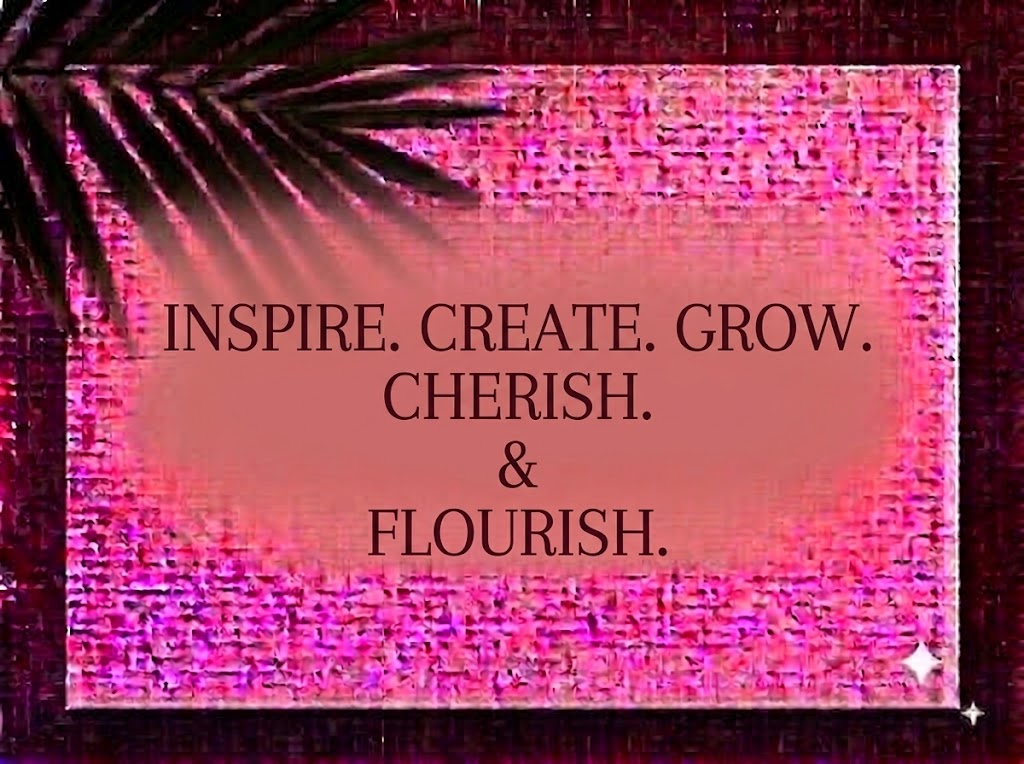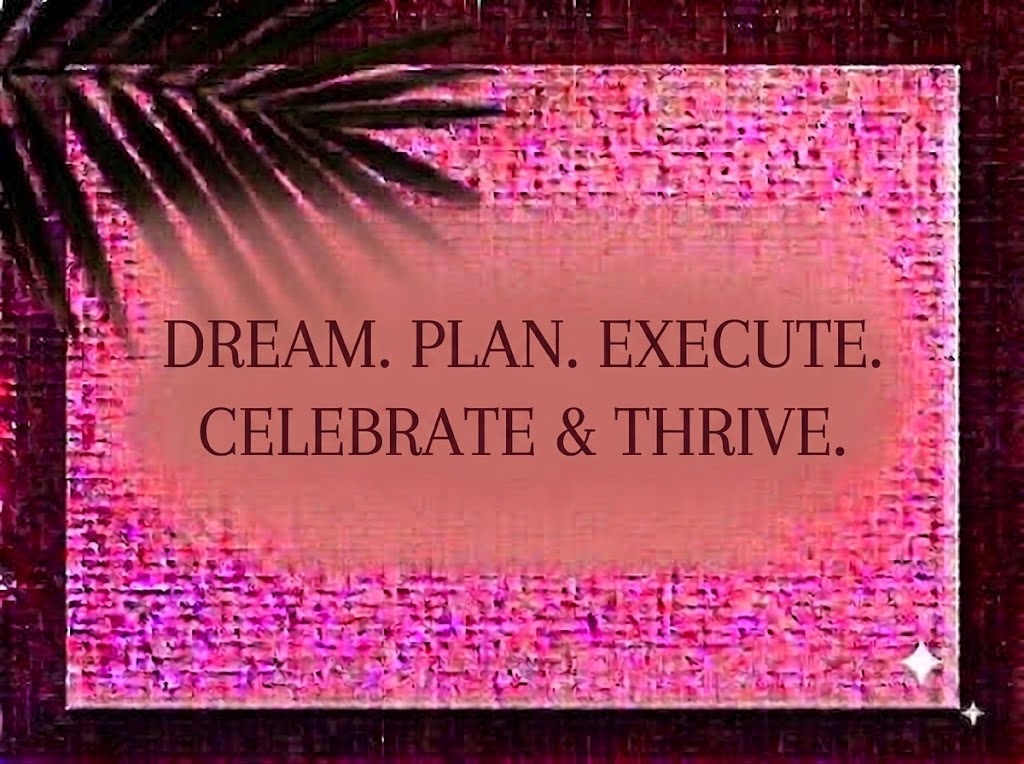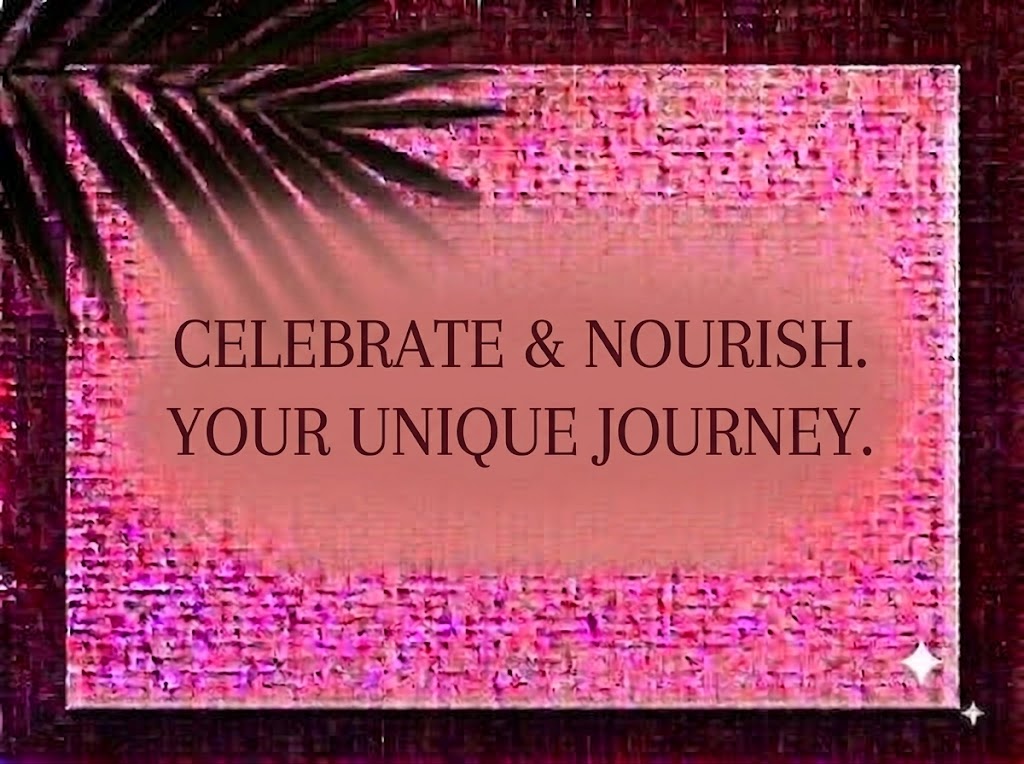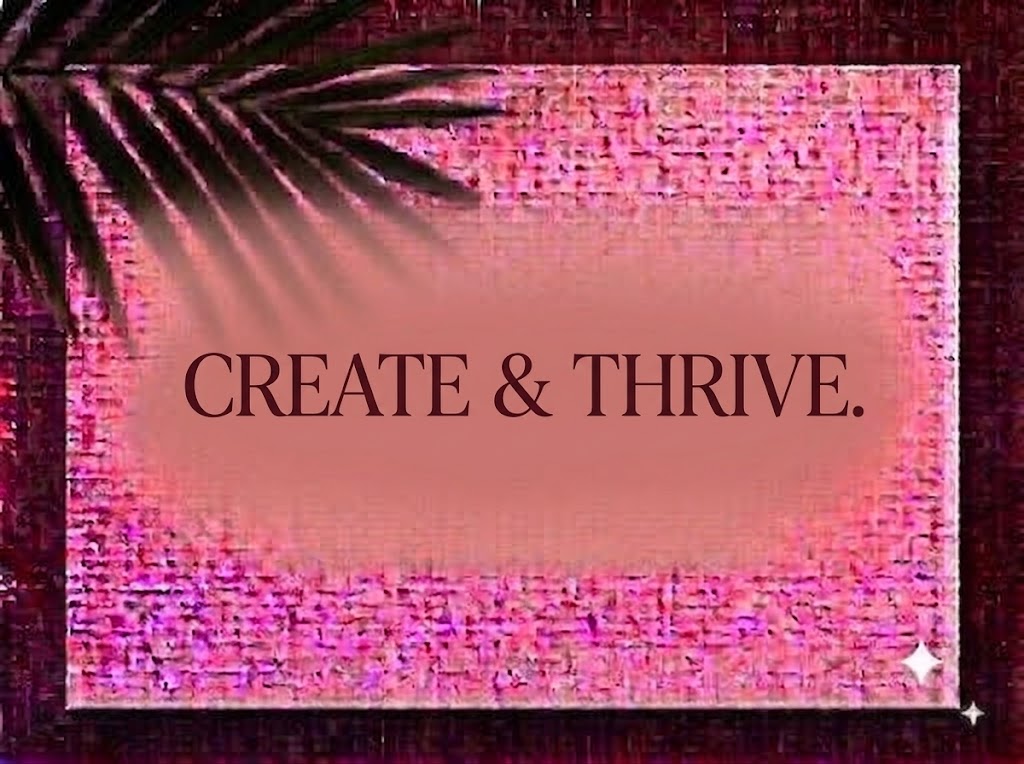
1FTV Magesta
Trong làn sóng thiết kế đồ họa cao cấp và dàn trang tạp chí thời trang đương đại (Editorial), những bộ phông chữ có chân hiển thị (Display Serif) mang đường nét biến điệu sắc sảo luôn giữ vị trí độc tôn trong việc khẳng định đẳng cấp.
Nếu bạn đang tìm kiếm một phông chữ Serif vừa đài các, vừa mang hơi thở thời trang Paris để làm logo thương hiệu thẩm mỹ, bìa lookbook, bao bì nước hoa hay tiêu đề video ngắn triệu view, font 1FTV Magesta chính là sự lựa chọn không thể bỏ qua.
Giới thiệu về font 1FTV Magesta
Font 1FTV Magesta là bộ chữ hiển thị có chân mang phong cách Modern Luxury Serif, nổi bật với sự kết hợp hài hòa giữa cấu trúc chữ thanh thoát và những nét vuốt nghệ thuật tinh xảo:
Tên phông chữ: 1FTV Magesta
Đặc điểm nổi bật của ngôn ngữ thiết kế Magesta
Sức hút thị giác của font 1FTV Magesta đến từ tỷ lệ chữ trang nhã cùng sự chăm chút kỹ lưỡng trong từng chi tiết tạo hình:
Chân Serif vát loe tinh xảo (Flared Serifs): Chân chữ không dùng khối chữ nhật thô cứng mà được vuốt loe nhẹ nhàng, kết hợp cùng các góc bo cong mềm mại ở các ký tự như
T,h,b,d,r,f… tạo nên nét chuyển động duyên dáng và tràn đầy sức sống. -
Biến điệu ký tự phá cách: Điểm nhấn thị giác đắt giá nằm ở chữ
kvới nhánh trên cách điệu lạ mắt, chữghai tầng cổ điển với tai chữ vểnh cao, cùng chữs,cuốn lượn sắc sảo, giúp dòng headline có chiều sâu nghệ thuật độc bản. -
Hệ thống chữ hoa và chữ thường đồng điệu: Dàn chữ cái in hoa uy nghi kết hợp nhịp nhàng cùng bộ chữ thường kiều diễm, tạo sự cân bằng hoàn hảo cho mọi bố cục typography.
Tối ưu hiển thị và dấu tiếng Việt từ 1FTV
Để phông chữ vận hành trơn tru trên cả hai hệ điều hành Windows và macOS, phiên bản này đã được tinh chỉnh kỹ lưỡng về mặt thông số nội tại:
Khoảng cách ký tự (Kerning): Khoảng hở giữa các chữ cái được tính toán cân bằng, đảm bảo các nét loe và đuôi chữ uốn lượn khi đứng cạnh nhau không bị va chạm hay rối mắt.
Bản Việt hóa chuẩn chỉnh: Hệ thống dấu thanh tiếng Việt (sắc, huyền, hỏi, ngã, nặng, mũ, móc) được trau chuốt thanh mảnh, đồng bộ với độ dày của thân chữ và đặt đúng trọng tâm thị giác, giúp các câu tiêu đề tiếng Việt giữ trọn vẹn nét trang nhã.
Đánh giá hiển thị thực tế
Khả năng hiển thị của phông chữ được tối ưu linh hoạt theo nhiều kích cỡ:
Kích thước nhỏ (12pt – 24pt): Nhờ cấu trúc khung chữ chuẩn mực và độ mở thoáng, các đoạn trích dẫn ngắn hay dãy số vẫn hiển thị rõ ràng trên màn hình di động.
Kích thước lớn (36pt – 72pt): Đây là đất diễn lý tưởng nhất để 1FTV Magesta phô diễn trọn vẹn độ tương phản cao, nét chân loe kiêu sa và thần thái sang trọng cho các dòng tiêu đề chính.
Ứng dụng trong thiết kế đồ họa và sản xuất video
Sở hữu nét cá tính quý phái và đậm chất thẩm mỹ thời trang, font 1FTV Magesta mở ra không gian ứng dụng phong phú:
Video ngắn (TikTok, Reels, Shorts): Dáng chữ Serif thanh lịch hiển thị rất cuốn hút trên khung hình đứng tỷ lệ 9:16. Cực kỳ ăn nhập với các vlog thời trang.
Ảnh thu nhỏ YouTube (Thumbnail): Lựa chọn tuyệt vời cho các kênh làm nội dung về làm đẹp, lifestyle, review đồ hiệu, podcast chữa lành hay âm nhạc acoustic lofi.
Nhận diện thương hiệu phân khúc Luxury: Hoàn hảo để thiết kế logo dạng chữ, bao bì nước hoa, mỹ phẩm organic, nến thơm, viện áo cưới hay menu nhà hàng fine dining.